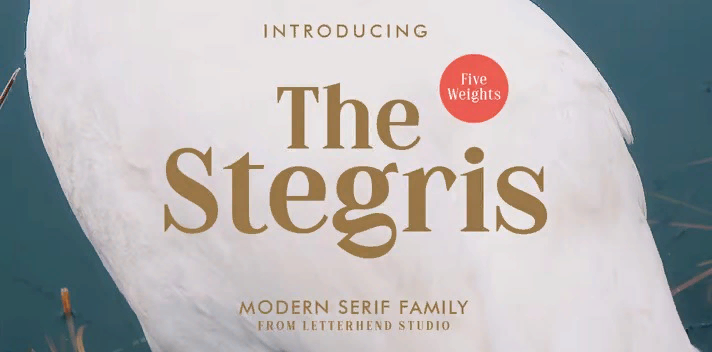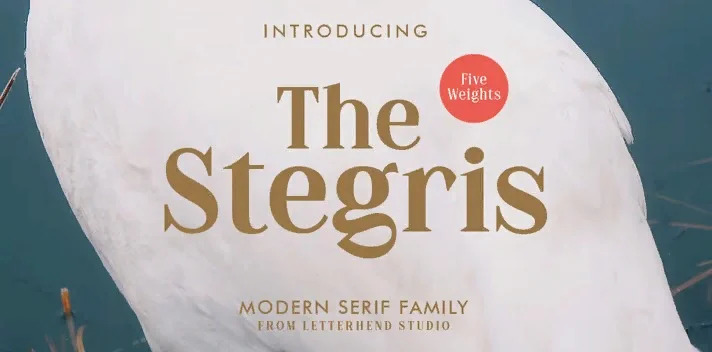
Название: The Stegris Font (2021)
Представляем вам семейство современных засечек Stegris.
Набор шрифтов с засечками и 5 весовыми категориями, которые можно выбрать в соответствии с вашими потребностями. Особенностью этого шрифта являются лигатуры, которые делают его еще более уникальным.
Этот тип шрифта идеально подходит для использования в логотипах и других различных формах, таких как приглашения, этикетки, логотипы, журналы, книги, поздравительные / свадебные открытки, упаковка, мода, макияж, канцелярские принадлежности, романы, этикетки или любые рекламные цели.